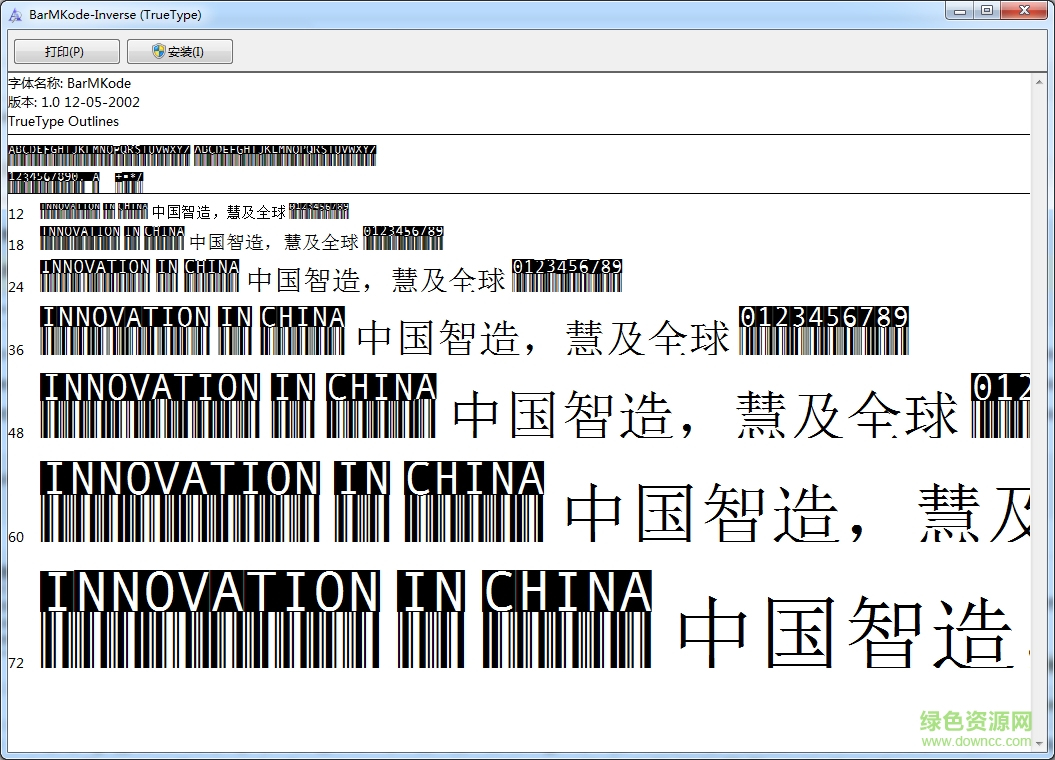
barmkodeinverse字體是一款非常好用的英文字體,在英文的字母元素上加入類似條形碼的元素,非常適合用于包裝行業(yè),歡迎有需要的朋友到綠色資源網(wǎng)下載使用!
這個字體設(shè)計的非常的奇葩,給人的視覺感受非常的別扭,小寫字母的特點, 大寫字母的對齊方式,導(dǎo)致很多負(fù)形空間的失衡,在設(shè)計的時候,沒有考慮到視覺 的整體性,所以看上去很不連貫,在設(shè)計的時候,作者只考慮到了字形筆畫特征的 統(tǒng)一,卻忽略了英文字體的基本規(guī)律,是對齊方式上,簡單的使用了物理對齊的方 式,殊不知視錯覺原理是文字設(shè)計必須考慮到的基本原理,所以這個字體看上去并 不整齊,反而顯得歪歪扭扭,拼湊感十足,這樣的字體作為企業(yè)形象拿到國際上去 宣傳,會給企業(yè)形象造成很大的負(fù)面影響,需要引起企業(yè)的足夠重視。